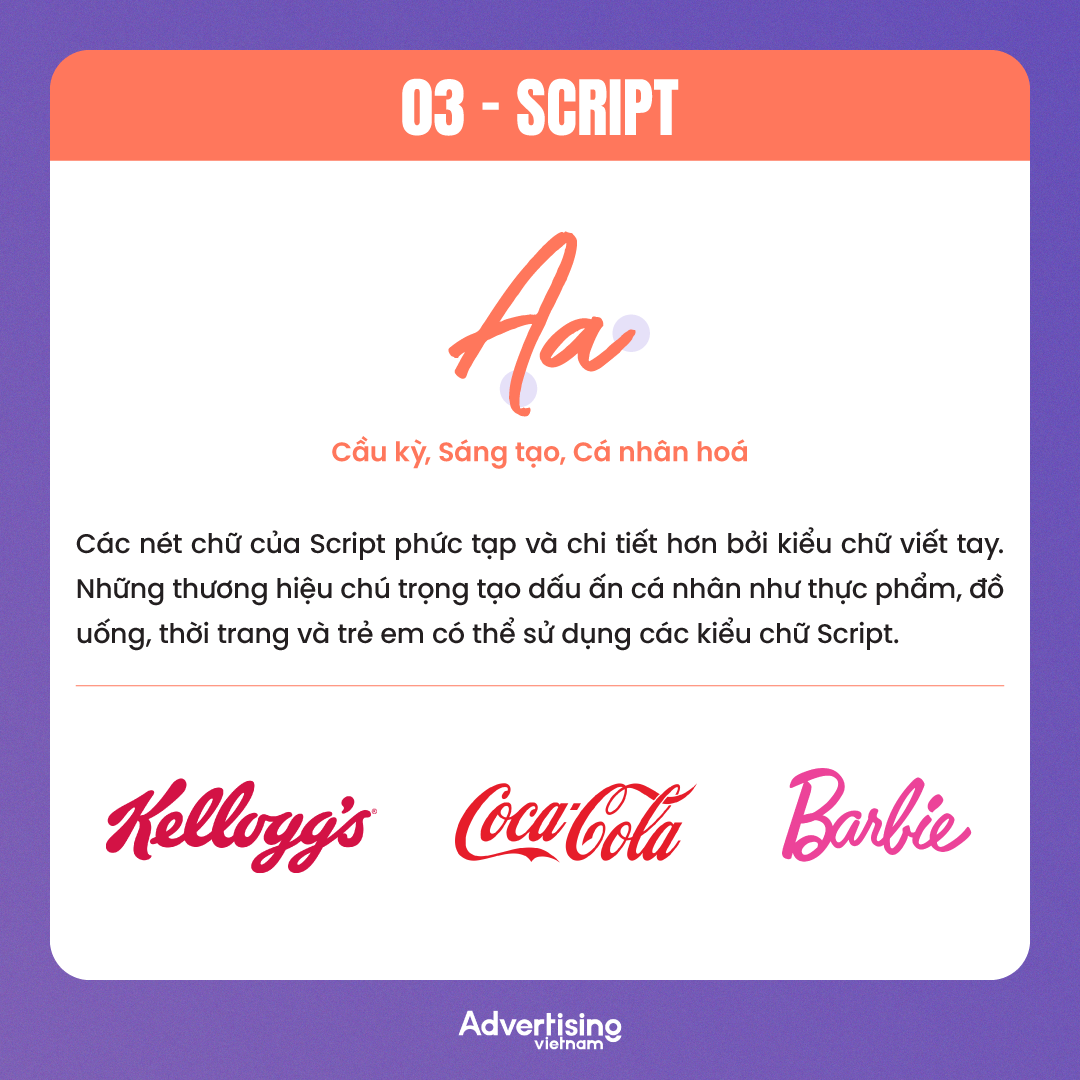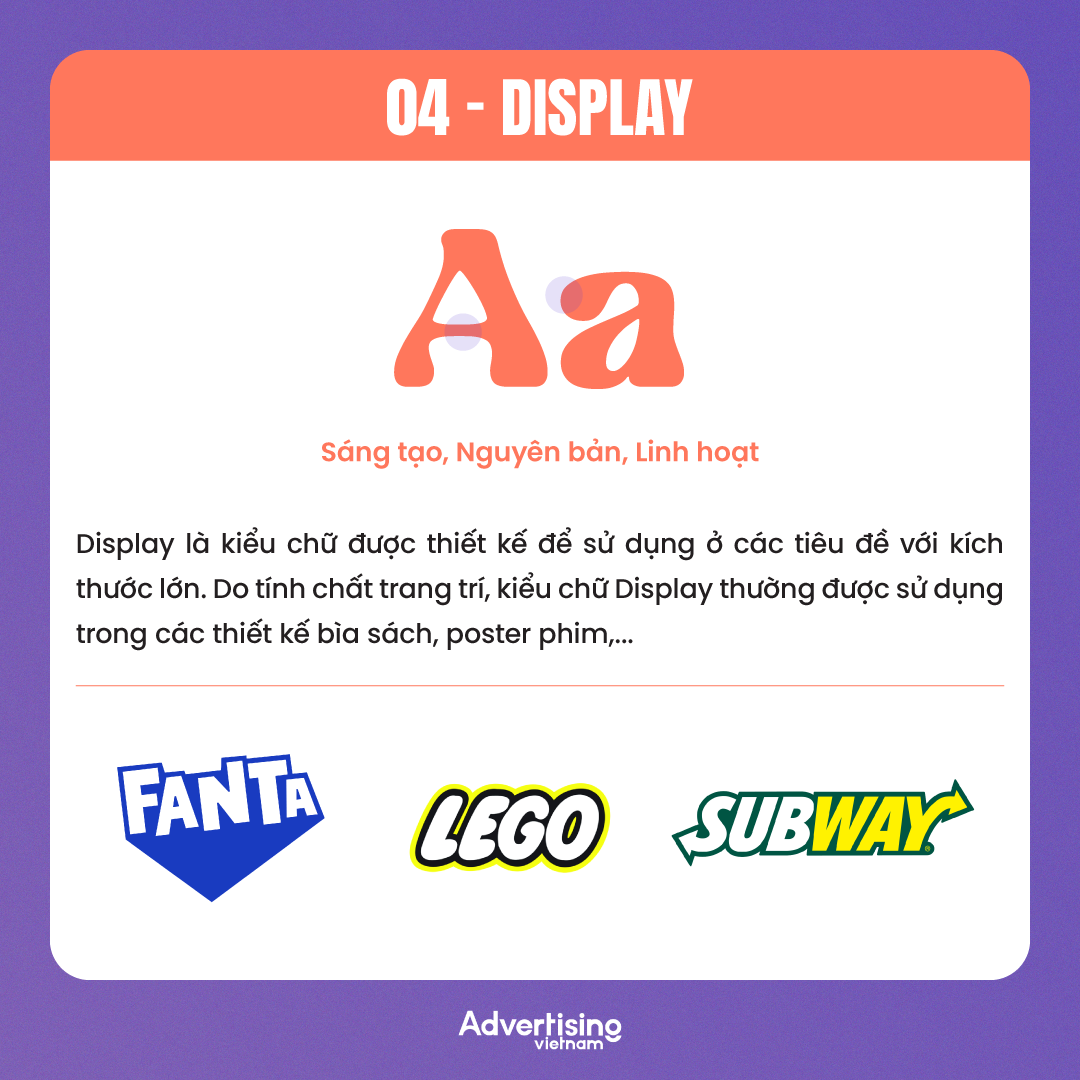
Trong quá trình xây dựng bộ nhận diện, có lẽ không ít marketer sẽ phải đau đầu khi lựa chọn typeface (kiểu chữ) phù hợp với giá trị và hình ảnh thương hiệu. Với hơn nửa triệu kiểu chữ trên thế giới, mỗi một kiểu chữ đều là phương thức giao tiếp bằng hình ảnh, tác động đến cảm xúc và nhận thức của con người về nội dung mà thương hiệu truyền tải. Do đó, việc tìm được một typeface phù hợp sẽ thúc đẩy trải nghiệm người dùng trên mọi điểm chạm, xây dựng tài sản thương hiệu, từ đó tạo ra trải nghiệm nhất quán khi người dùng tiếp xúc với thương hiệu.
Tuy nhiên, đầu tiên người dùng cần phân biệt được hai thuật ngữ là “typeface” và “font”. Cụ thể, “typeface” được dùng để chỉ phong cách, kiểu thiết kế, nhận diện của một bộ chữ, đơn cử như Arial, Times New Roman, Helvetica,... Trong khi đó, “font” là từ để chỉ hình thái của bộ chữ đó, ví dụ như Arial Bold (Arial in đậm), Arial Italic (Arial in nghiêng),...
Tiếp đó, bằng cách tìm hiểu về ý nghĩa của vô vàn kiểu chữ khác nhau, các nhà thiết kế và marketer có thể đưa ra quyết định đúng đắn trong quá trình lựa chọn. Cùng xem xét sâu hơn về lịch sử và tác động của các kiểu chữ ở cấp độ tâm lý qua bài viết sau!
Lịch sử của các kiểu chữ
Trước khi ông Johannes Gutenberg - thợ hoàn kim, nhà xuất bản người Đức phát minh ra máy in vào giữa thế kỷ 15, các quyển sách được viết bằng tay. Khi ấy, ông Gutenberg nhận ra rằng việc sản xuất sách hàng loạt có triển vọng sinh lời nhanh chóng hơn so với phương pháp thủ công. Vì thế, ông đã kết hợp loại máy di động được sử dụng ở Đông Á và máy ép trục vít được nông dân ở Châu Âu sử dụng lúc bấy giờ để tạo ra chiếc máy in đầu tiên.
Vào thời điểm ấy, Blackletter là kiểu chữ (typeface) tiêu chuẩn để in ấn bởi chúng mô phỏng cách viết tay thời bấy giờ. Chúng gợi nhắc đến những bản thảo chép tay của các học giả thời Trung Cổ với ngòi bút viết rộng và thẳng. Tuy nhiên, cấu trúc chữ cái của Blackletter tương đối phức tạp và dày đặc, chiếm không gian đáng kể trên trang, từ đó giới hạn số lượng văn bản có thể vừa trên một trang, khiến những quyển sách trở nên quá dày.
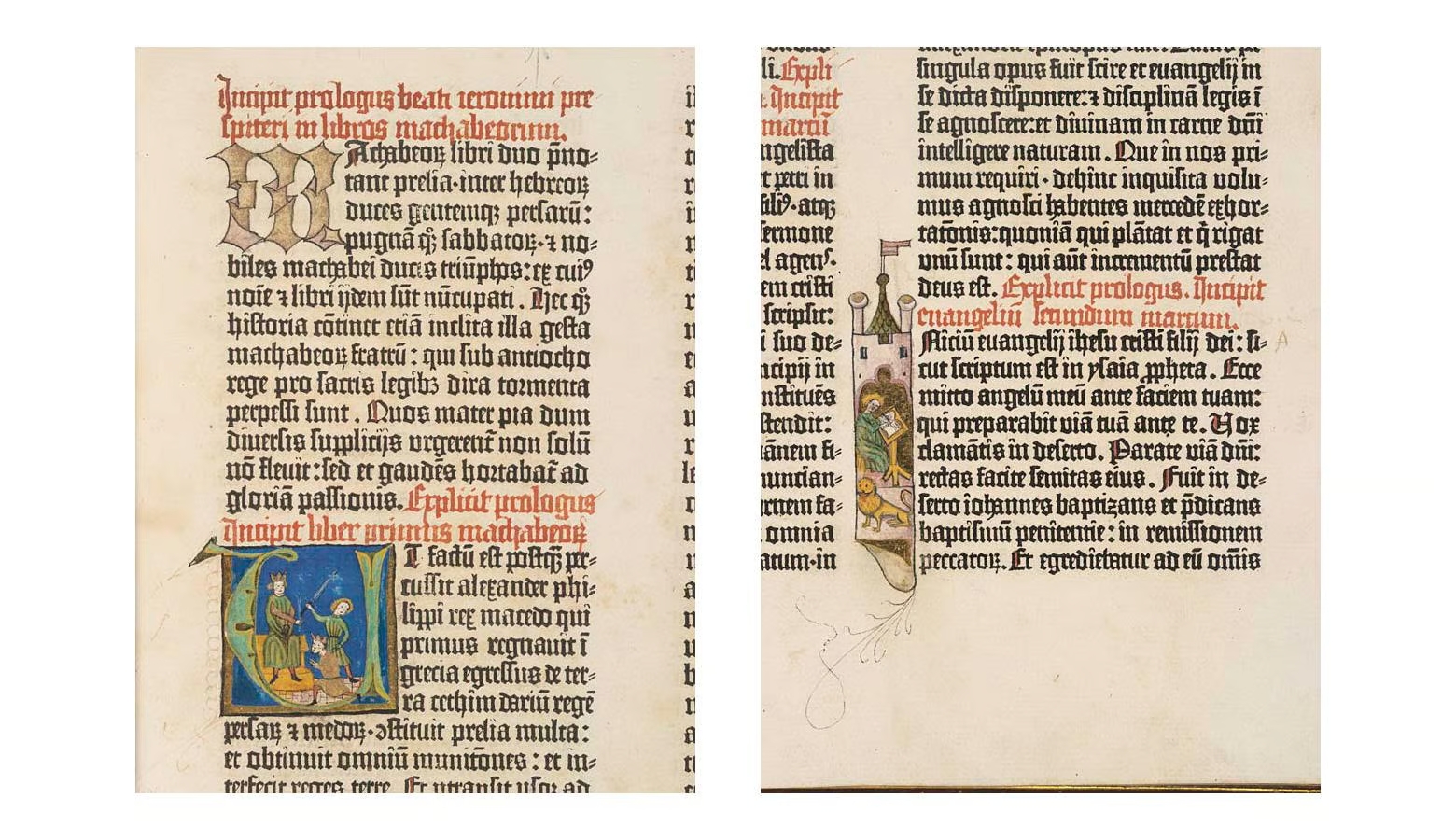
Vì thế, đến năm 1470, ông Nicolas Jenson - nhà in và nhà thiết kế người Pháp nhận ra rằng các dạng chữ đơn giản sẽ có thể chứa được nhiều văn bản hơn trên một trang, dẫn đến những cuốn sách ngắn hơn cùng thời gian sản xuất nhanh chóng hơn. Đó là lý do mà ông đã tạo ra typeface La Mã đầu tiên, dựa trên kiểu chữ Blackletter và kiểu chữ Italian Humanist. Đây cũng là nền tảng cho nhiều kiểu chữ hiện đại khác như Centaur, Adobe Jenson,...
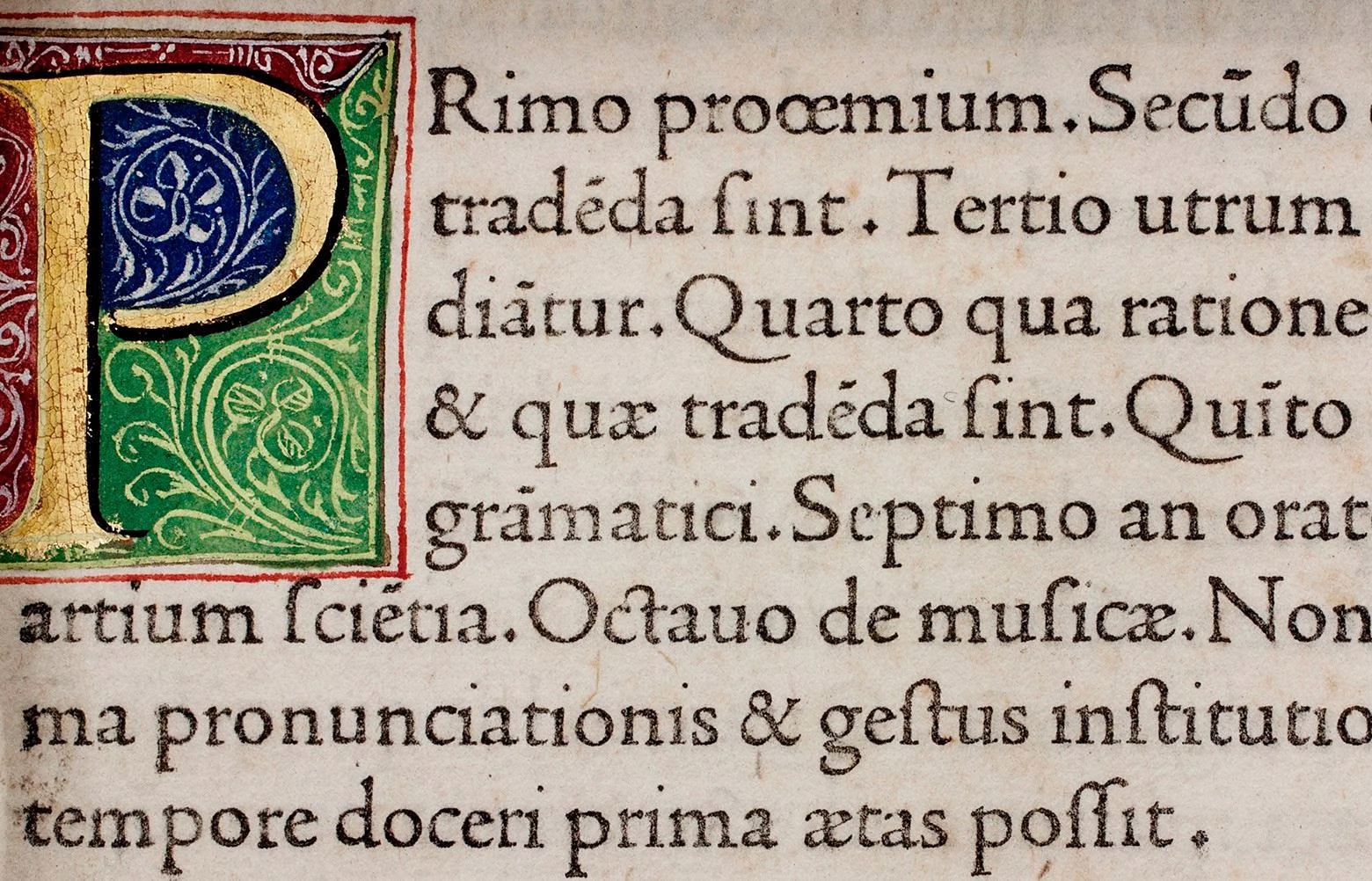
Kiểu chữ La Mã đầu tiên do Nicolas Jenson phát minh
Trong khi kiểu chữ La Mã của Jenson đã góp phần tiết kiệm không gian trên trang in, những nhà thiết kế khác lại muốn tiếp tục cải thiện hiệu quả của việc in sách. Năm 1501, Aldus Manutius và Francesco Griffo đã tạo ra kiểu chữ in nghiêng đầu tiên, cho phép 1 trang có nhiều nội dung hơn. Mặc dù ban đầu được phát minh như một biện pháp tiết kiệm không gian, song nhiều nhà xuất bản vẫn sử dụng chữ in nghiêng để nhấn mạnh các đoạn thông tin quan trọng.
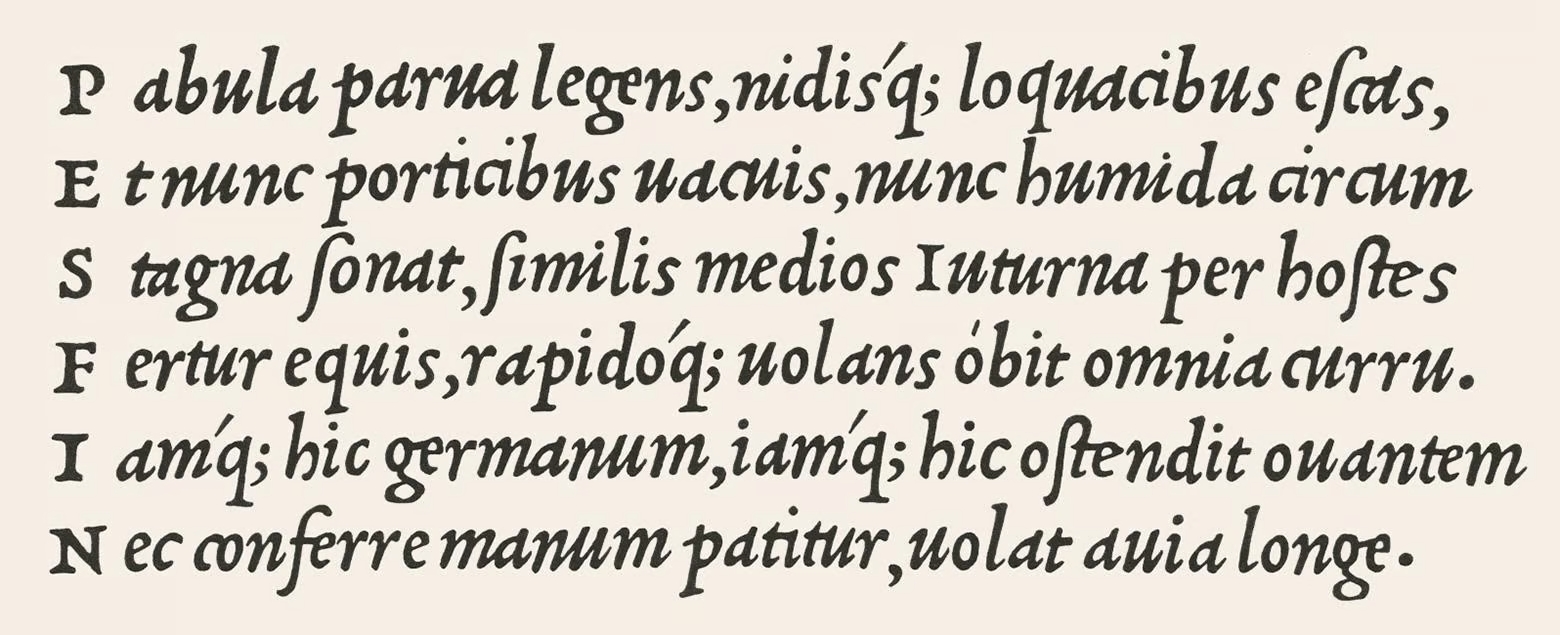
Sau thời gian dài phát triển, hiện nay các nhà thiết kế có bốn cách phân loại kiểu chữ cơ bản là Serif, Sans Serif, Script và Display.
Bốn kiểu chữ phổ biến hiện nay
1. Serif Typeface
Serif là một trong những kiểu chữ cổ điển nhất, với đặc điểm nổi bật là phần nhô nhẹ ở đoạn cuối của các chữ cái, khiến Serif nổi tiếng với tên gọi “chữ có chân”. Các kiểu chữ Serif phổ biến nhất hiện nay có thể kể đến như Times New Roman, Georgia, Palantino,...
Theo Canva, Serif rất phù hợp với các doanh nghiệp truyền thống, bao gồm công ty tài chính, luật, bảo hiểm và tư vấn. Khi sử dụng kiểu chữ Serif trong thiết kế, thương hiệu sẽ tạo cho người dùng cảm giác rằng họ là một công ty truyền thống và lâu đời. Một số liên tưởng cảm xúc mà Serif truyền tải đến người dùng bao gồm:
- Lòng tin
- Sự tôn trọng
- Thẩm quyền
Các thương hiệu như Rolex, ZARA, Vogue và Sony đã sử dụng Serif để sáng tạo logo. Với Rolex, logo của hãng sử dụng phiên bản đặc biệt của “Cyclo” hoặc “Cyclo New” - một loại kiểu chữ Serif truyền thống với nét đậm và cân đối. Việc sử dụng kiểu chữ này tạo nên cảm giác của sang trọng, đẳng cấp và lịch lãm, phù hợp với hình ảnh một thương hiệu đồng hồ cao cấp. Còn với ZARA, thương hiệu sử dụng kiểu chữ “ZARA Custom” mang đến cảm giác hiện đại, sáng tạo và đơn giản. Kiểu chữ này thường được kết hợp với việc sắp xếp các chữ cái gần nhau, tạo nên một hình ảnh thân thiện trong mắt người tiêu dùng.
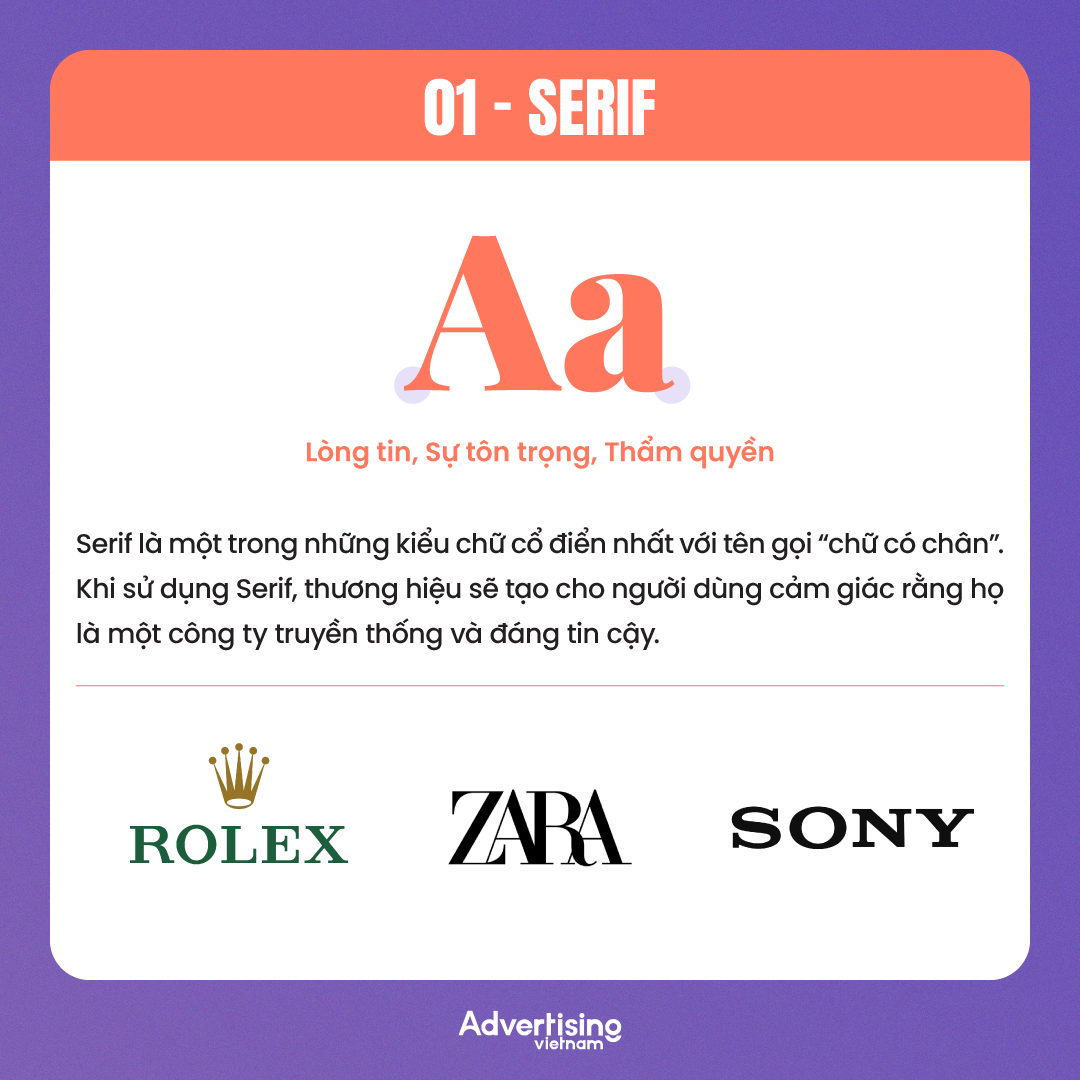
2. Sans Serif Typeface
Các nhà thiết kế có thể xem kiểu chữ Sans Serif như một bản nâng cấp của Serif. Theo nghĩa Latin, Sans Serif có nghĩa là "without serif", tức là kiểu chữ không có chân, có thể kể đến Arial, Helvetica, Futura và Calibri.
Khi thương hiệu sử dụng kiểu chữ này, người dùng sẽ cảm nhận được các yếu tố:
- Hiện đại
- Đơn giản
- Công nghệ
Vì thế, có thể nói Sans Serif rất phù hợp với những thương hiệu muốn thiết kế của họ sáng tạo và tinh tế hơn trong mắt người dùng. Đơn cử như công ty công nghệ, thời trang, các doanh nghiệp start-up,...
Một ví dụ điển hình cho việc dùng kiểu chữ Sans Serif để sáng tạo logo là Google. Vào những năm 2000, Google đã sử dụng kiểu chữ Serif trên logo nhằm chứng minh họ là cổng thông tin truy cập Internet chính xác và uy tín. Thế nhưng theo thời gian, Google dần trở nên phổ biến trên toàn cầu. Vì thế, họ không cần phải sử dụng Serif nữa. Đó là lý do tập đoàn đã chuyển sang sử dụng typeface Sans Serif vào năm 2015 nhằm mang đến cảm giác hiện đại hơn.
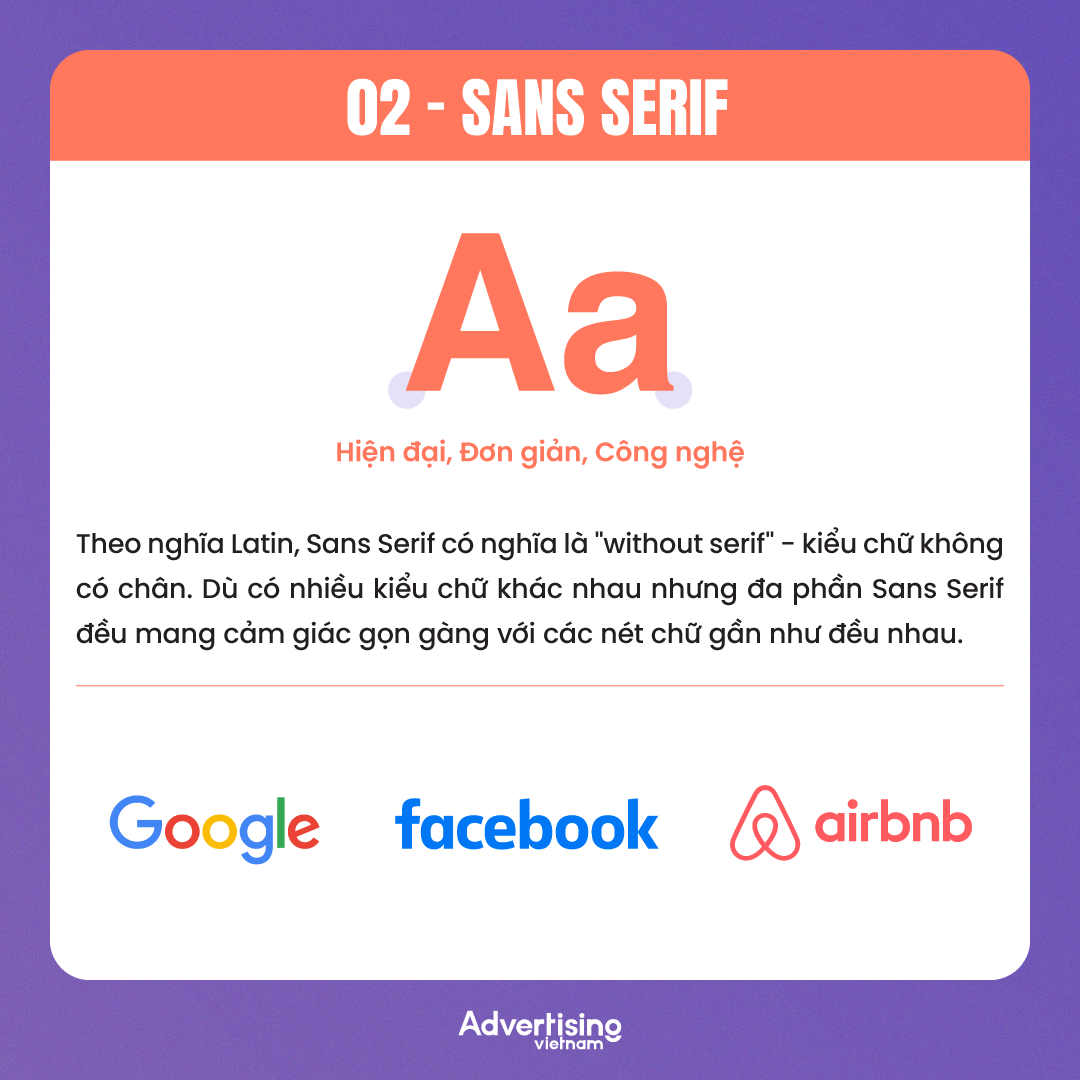
Chọn sai kiểu chữ có thể thay đổi hoàn toàn giao diện thiết kế, khiến cách khán giả phản ứng trái ngược hoàn toàn với mong muốn của thương hiệu. Nếu đang thiết kế ảnh bìa Facebook để quảng cáo cho công ty tư vấn tài chính, thương hiệu sẽ muốn truyền tải cảm giác tin cậy và ổn định cho người dùng.
Vì thế, dựa trên tính cách và thông điệp muốn truyền tải đến người dùng, các thương hiệu có thể lựa chọn kiểu chữ phù hợp, góp phần mang lại cảm giác tin tưởng cho đối tượng mục tiêu.